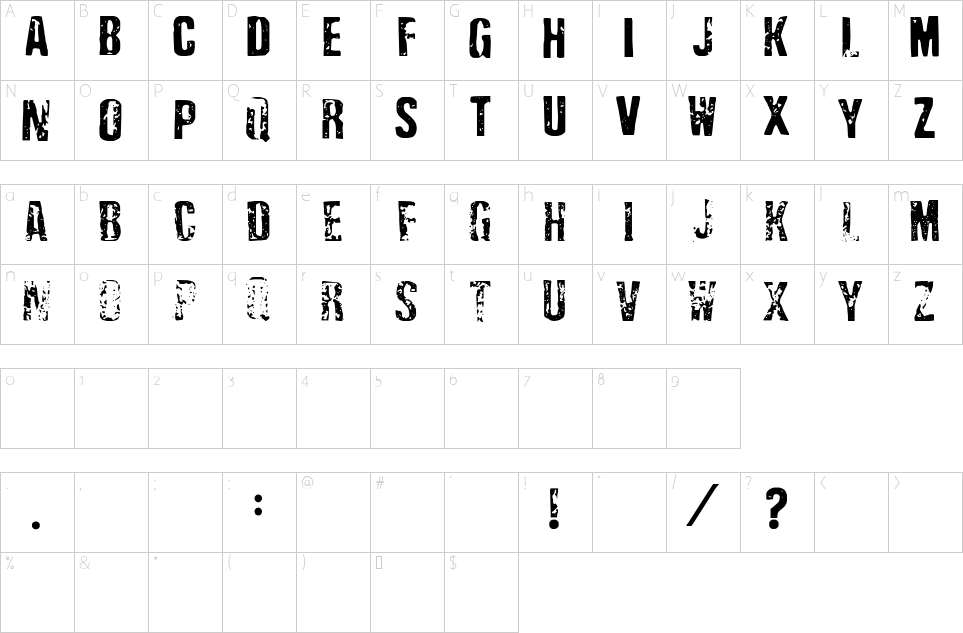
Aqui está uma descrição em português para a página de download da fonte ‘Depressionist Three Font’, seguindo as instruções: Através do site Depressão, encontramos um conjunto de 3 caracteres únicos e inusitados chamado Depressionist Three. Desenhada por Mr Fisk, esta fonte se destaca pela sua aparente simplicidade e intensidade única. Com aparência atraente e versatilidade, é uma escolha ideal para designers interessados em adicionar um toque único ao seu trabalho gráfico. Não se preocupe, pois esta fonte pode ser baixada gratuitamente tanto para o Windows quanto para o Mac. Depressionist Three já teve 3503 downloads e continua a ser um dos recursos mais populares do site Depressão. Este design minimalista, com suas linhas fortes e harmoniosas, pode tornar seu design mais atrativo sem comprometer sua funcionalidade. Adicioná-la ao seu projeto certamente dará uma dose de originalidade e criatividade que tanto os profissionais quanto os amantes do design valorizam.